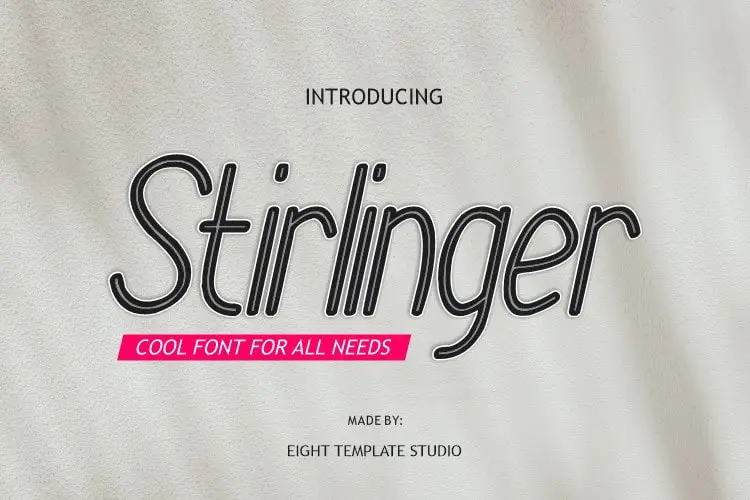
Stirlinger Sans Serif Font – Download Grátis
A Stirlinger Sans Serif é uma fonte sans-serif minimal e prazerosamente limpa. Com uma design leve e eficiente, ela se integra facilmente a uma ampla variedade de projetos, tornando-as ainda mais atraentes e chamativas. Seja para um layout editorial, uma arte digital ou até mesmo para criar gráficos em papel impresso, esta fonte estará sempre à mão para dar aquele toque especial aos seus trabalhos. Com o Stirlinger Sans Serif Font de kumsstudio, sua criatividade ganha mais um alicerce para explorar e inovar, garantindo que suas ideias sejam percebidas de forma impactante e memorável.